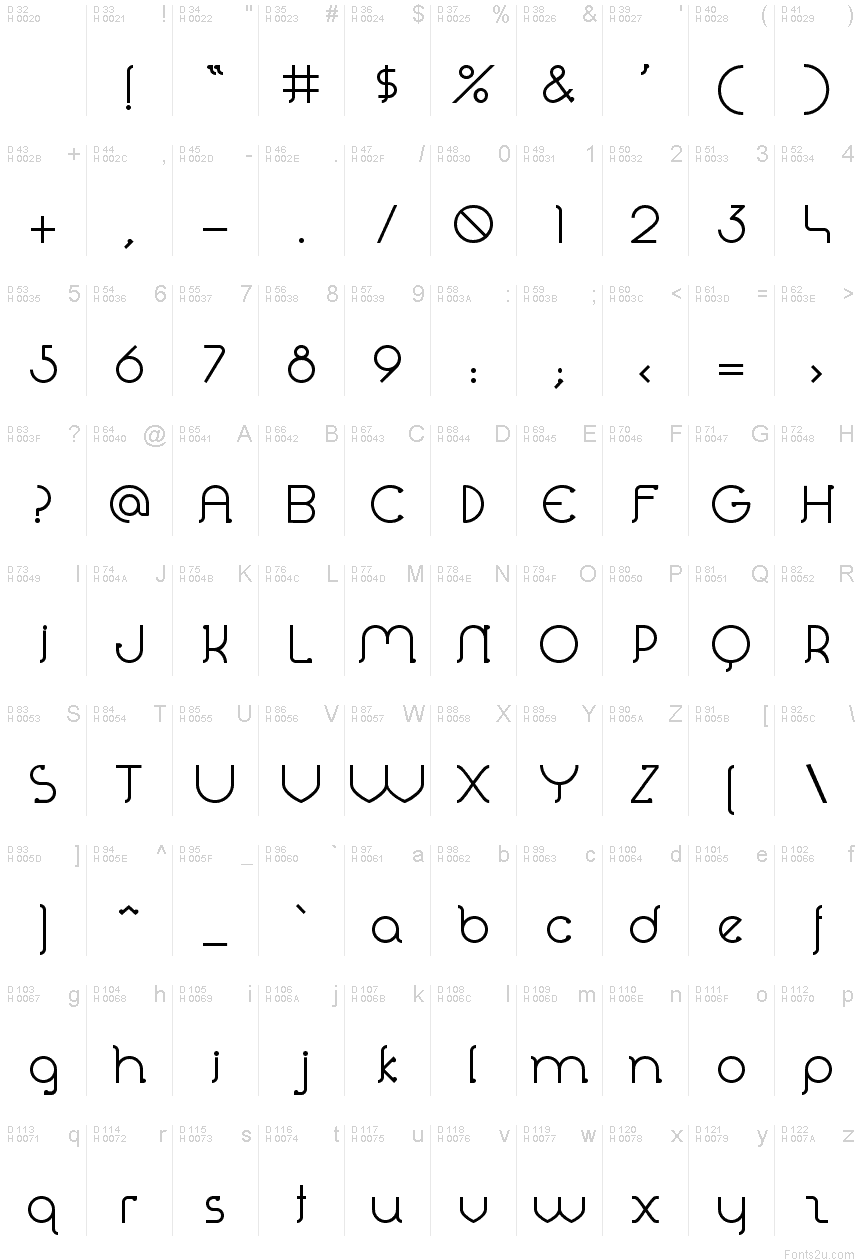
Perolet è un font display gratuito in stile Art Nouveau, caratterizzato da un ritmo leggero e sinuoso, costruito con lettere quasi monolinea e forme circolari morbide. Il design è decorativo senza risultare complicato: la "o" rotonda, la "e" arricciata e l'uncino netto sulla "r" conferiscono al font un'eleganza che evoca i manifesti dell'inizio del XX secolo.
È l'ideale dove un titolo deve creare atmosfera: branding di boutique, menu di caffè, copertine di libri, packaging e titoli editoriali sono perfetti per questo font gratuito. Usalo per parole brevi, iniziali o cartelli quando vuoi che siano le lettere stesse a portare un tocco ornamentale.